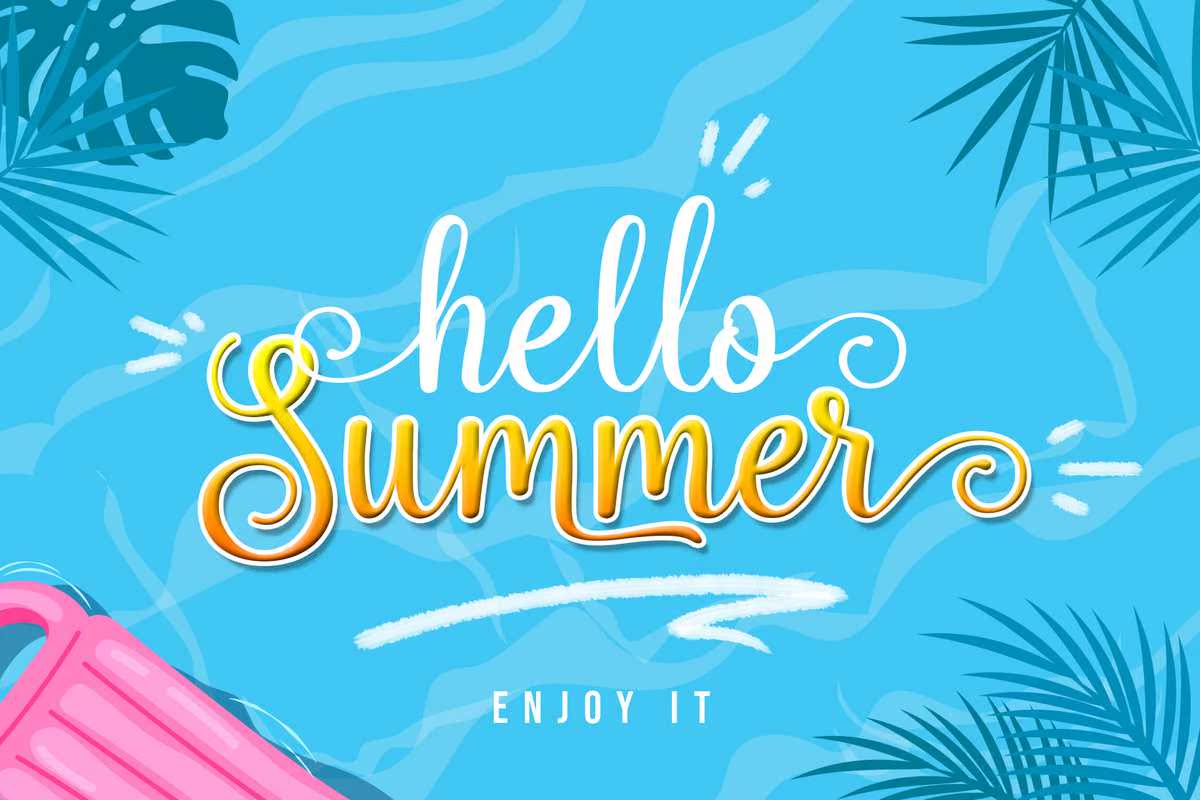
HellosWeety是由730+交替字符和连字组成的优雅字符;这是给你带来敏感和浪漫的最佳方式。它的特点是装饰性角色和舞蹈基线!。HellosWeety适用于品牌项目、徽标、婚礼设计、社交媒体、广告、产品包装、产品设计、标签、摄影、水印、邀请函、文具以及任何需要精美书法的项目。HellosWeety是由730+可选字符和连字组成的精美字体;这是给你带来敏感和浪漫的最佳方式。它的特点是装饰性角色和舞蹈基线!。HellosWeety适用于品牌项目、徽标、婚礼设计、社交媒体、广告、产品包装、产品设计、标签、摄影、水印、邀请函、文具和任何需要精美书法的项目。